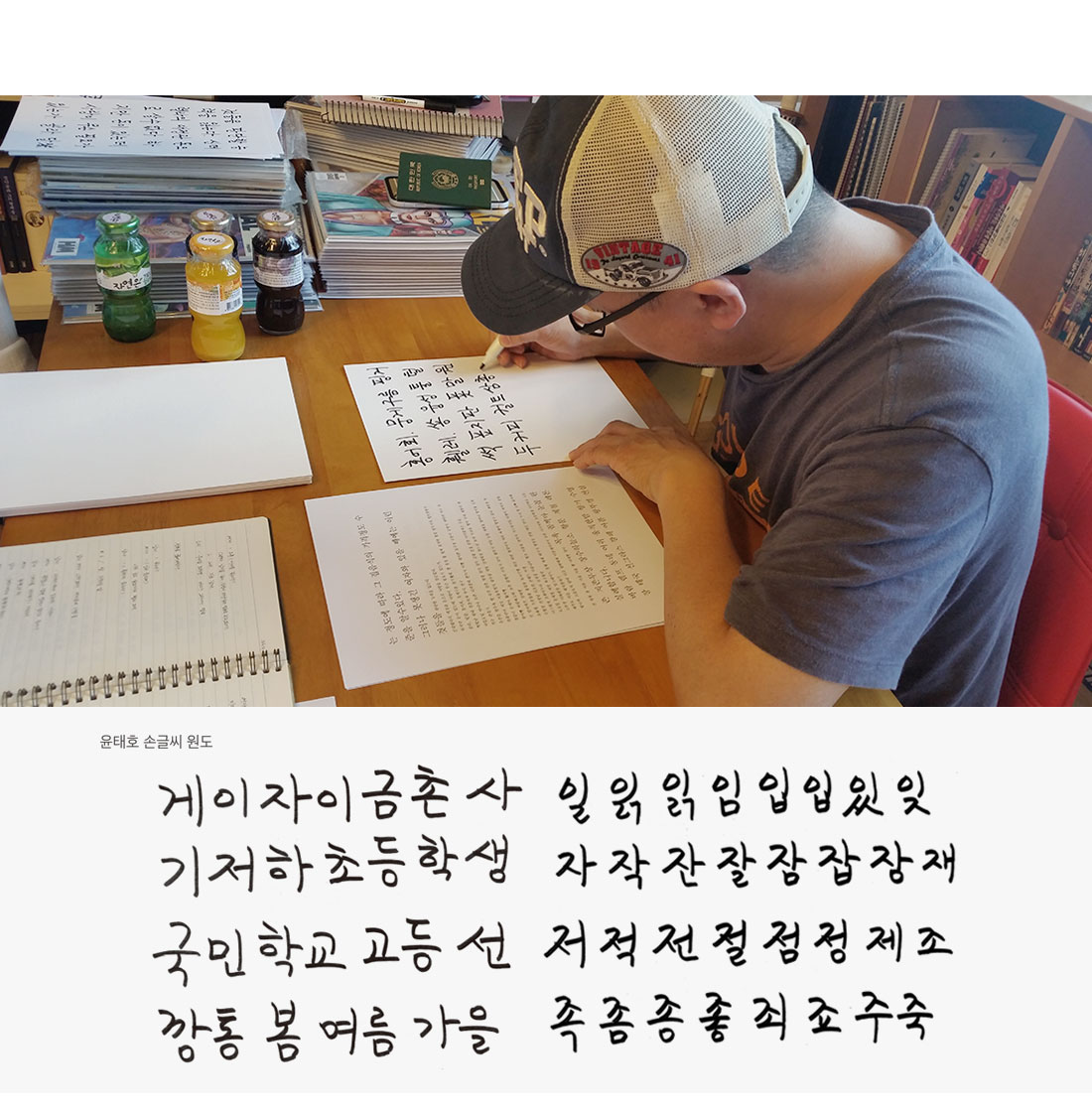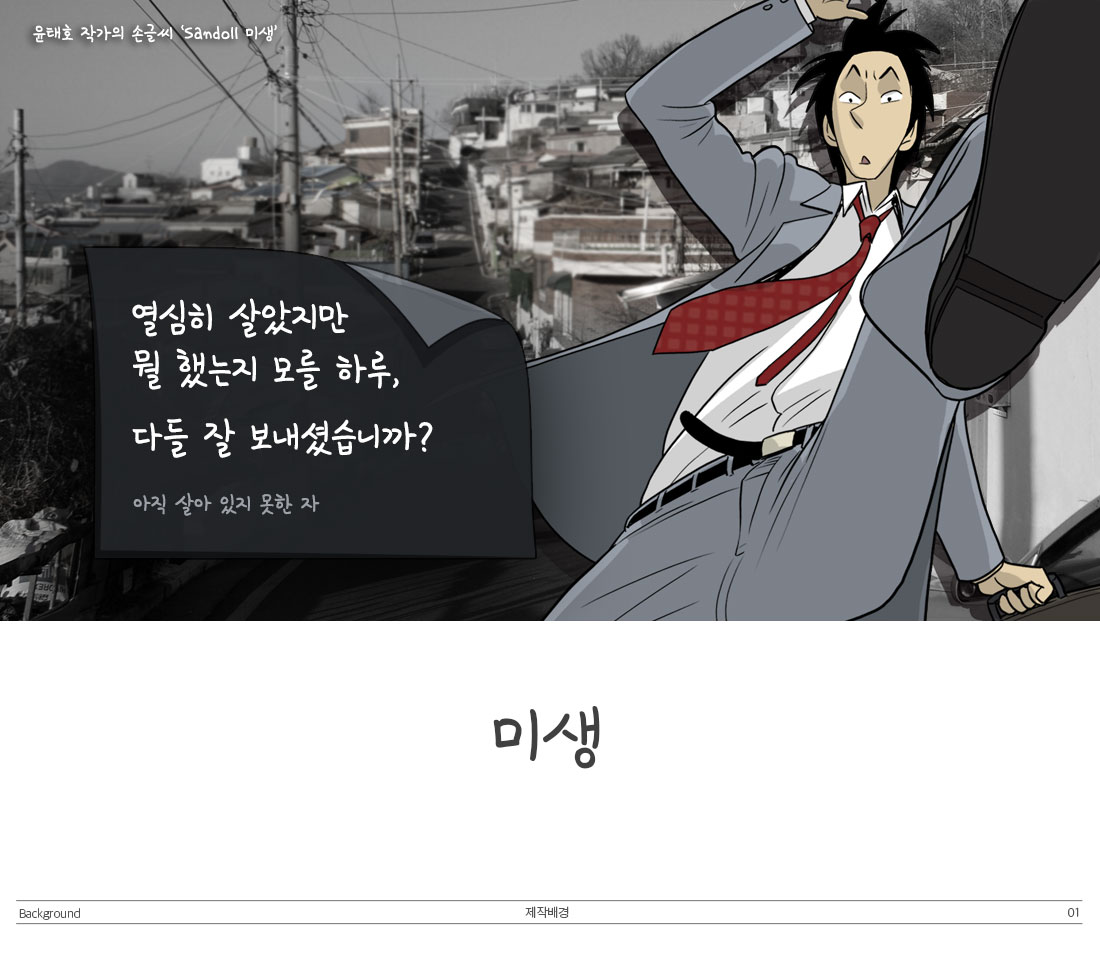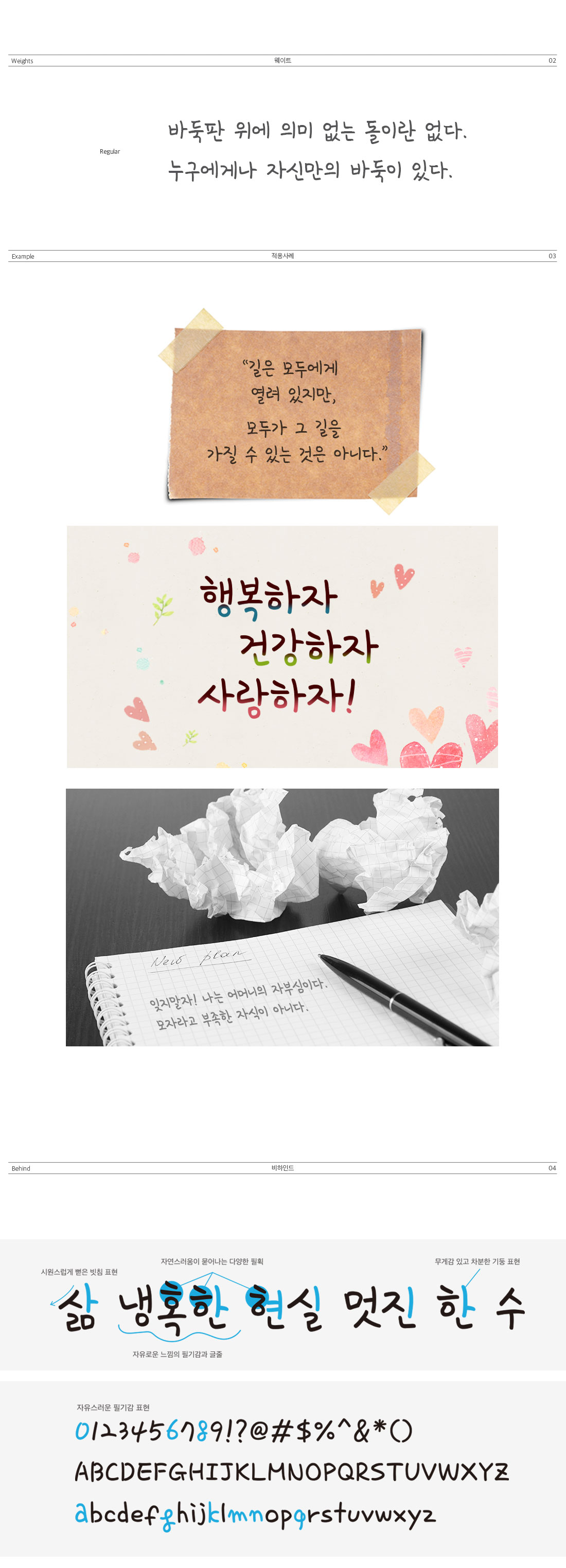
산돌, 윤태호 작가의 손글씨로 만든 ‘미생체’ 출시
산돌커뮤니케이션이 윤태호 작가의 손글씨로 만든 폰트, 미생체를 출시했다. 이 시대의 모든 미생들을 위해 제작된 폰트로, 윤태호 작가와 카카오, 산돌의 협업으로 진행되었다. 아마추어 작가나 프리랜서 디자이너 등 영세한 창작자들을 지원하기 위해 시작된 프로젝트인만큼 개인과 기업 누구라도 사용목적에 관계없이 사용이 가능해 부담없이 이용할 수 있다.
폰트와 저작권, 어쩐지 먼 이야기같지만 그 안을 들여다 보면 우리의 삶과 밀접하게 관련되어 있다. 비단 웹툰 작가들이나 디자이너가 아니어도, 무언가를 쓰는 모든 것은 폰트와 연관되어 있다고 할 수 있다.
윤태호 작가는 수많은 웹툰 작가들이 저작권이나 유료 서체에 대한 부담감을 가지고 있다는 사실을 누구보다도 잘 알고 있었다. 무수한 고민 끝에 웹툰 작가들은 물론 구매력이 확보되지 않은 일반인들도 공공재처럼 사용 할 수 있는 폰트를 꿈꿨다. Sandoll 미생은 프리랜서 창작자, 아마추어 작가들, 영세한 디자이너들을 위한 ‘진짜’ 무료 폰트를 만들자는 생각에서 시작하였다. 윤태호 작가, 다음카카오, 산돌이 함께 Sandoll 미생을 만들었다.
# 화려함 보다는 자연스러움으로
Sandoll 미생은 다른 작가 폰트들처럼 화려하거나 독특한 개성을 지니고 있지는 않지만, 윤태호 작가 손글씨 특유의 자연스러움이 있다. 둥근 네임펜으로 정성스럽게 써내려간 손글씨에 어떠한 변형도 가하지 않아서, 부드러운 질감과 다양한 필획에서 자유로운 글줄에서 자연스러움이 뭍어나는 것도 이 때문이다.
# 한 자 한 자, 정성을 담은 손글씨
줄곧 그림만 그리며 살아왔다는 윤태호 작가는 사실 글씨가 엉망이었다. 그래서 의도적으로 글씨와 친해지기 위해서 매일같이 글씨를 썼다. 원고지 형식에 맞춰서, 한 자 한 자, 또박 또박, 정성스럽게 써내려갔다. 그렇게 스스로에게 벌을 주듯 써내려간 글씨는 지금의 윤태호 작가의 손글씨이자, Sandoll 미생의 원도가 되었다.
# Sandoll 윤태호가 아닌 Sandoll 미생인 이유
일반적으로 작가 폰트의 경우 작가 이름을 넣는다. 하지만 Sandoll 미생의 경우, 윤태호가 아닌 미생으로 이름지어졌다. 그 이유는 윤태호 작가 스스로 부끄럽고 민망스러워 한 이유도 있었지만, 작가(윤태호)보다는 작품(미생)이 주는 느낌에 주목했기 때문이다. 값비싸 보이진 않지만, 편안하고 일상적인 느낌의 Sanoll 미생은 일상의 사소한 기억과 잘 어울린다.
윤태호 작가 역시, 격언, 잠언, 메모 등에 어울릴 폰트라고 전했다. 누구라도 유용하게 써주면 좋겠다는 윤태호 작가의 바람처럼 저작권 걱정 없이 퀄리티 좋은 서체를 누구나 부담 없이 사용 할 수 있는 폰트, Sandoll 미생이다.